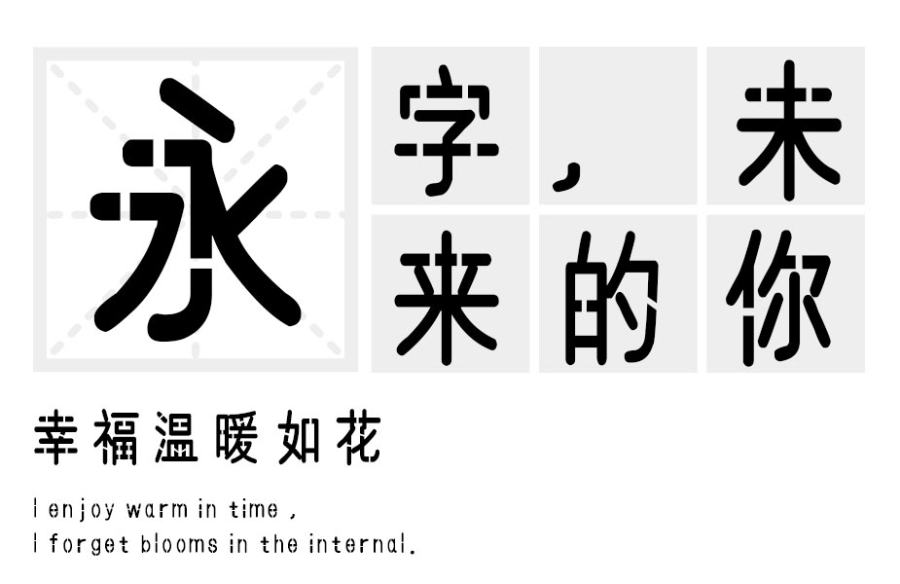
汉标断筋大圆字体发布
字体名称:汉标断筋大圆
字体类别: 创意字体
汉标断筋字体简介:根据圆体的字形创作而来,作者通过大量字体截断设计,使得字体有断筋感,从而展现美术视觉感,蕴含着深沉的艺术魅力,能给人以无限的美感,适合应用于艺术设计、平面宣传、包装印刷、图形设计、网页设计、书法字帖等领域。
汉标断筋大圆字体预览图展示: